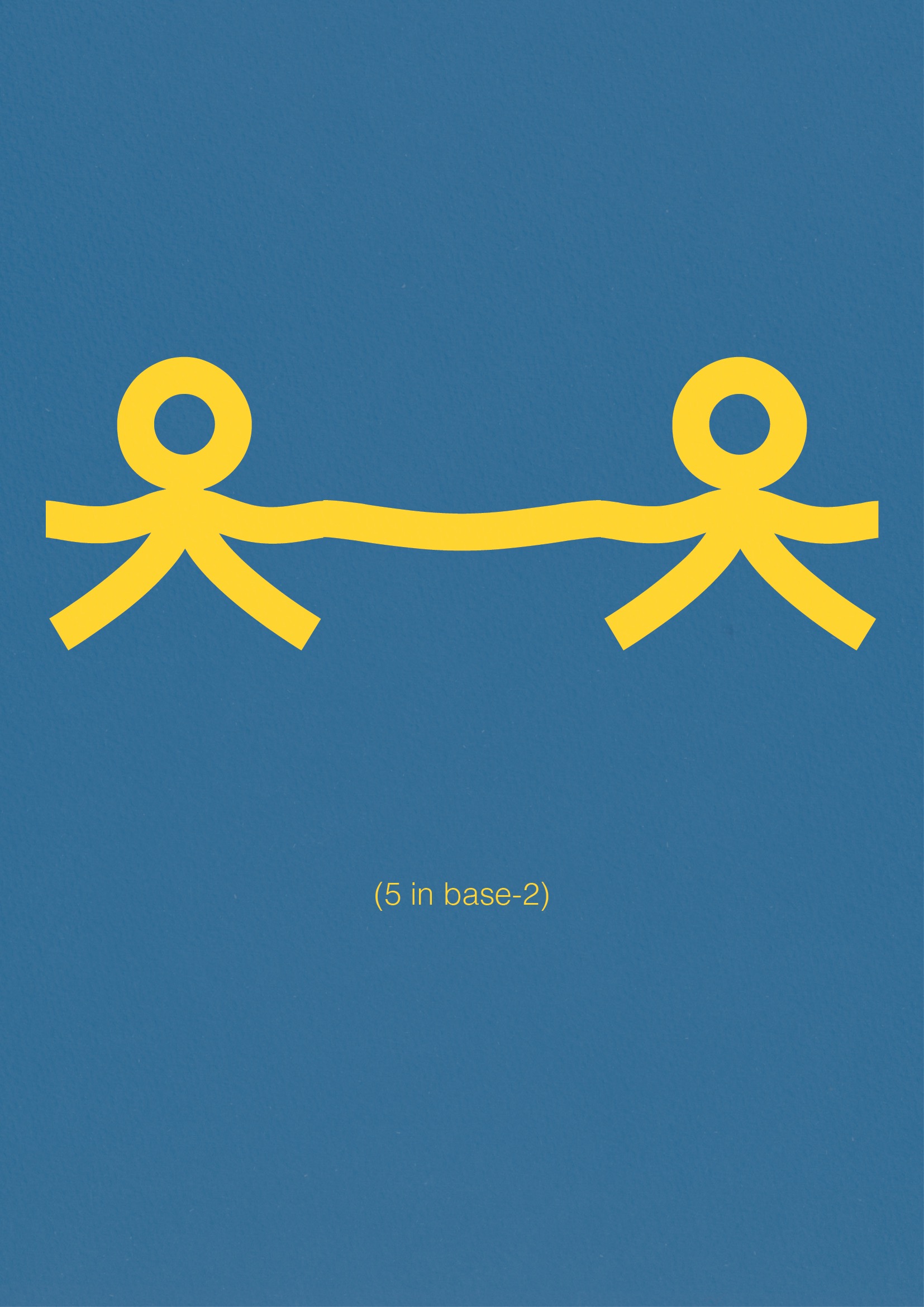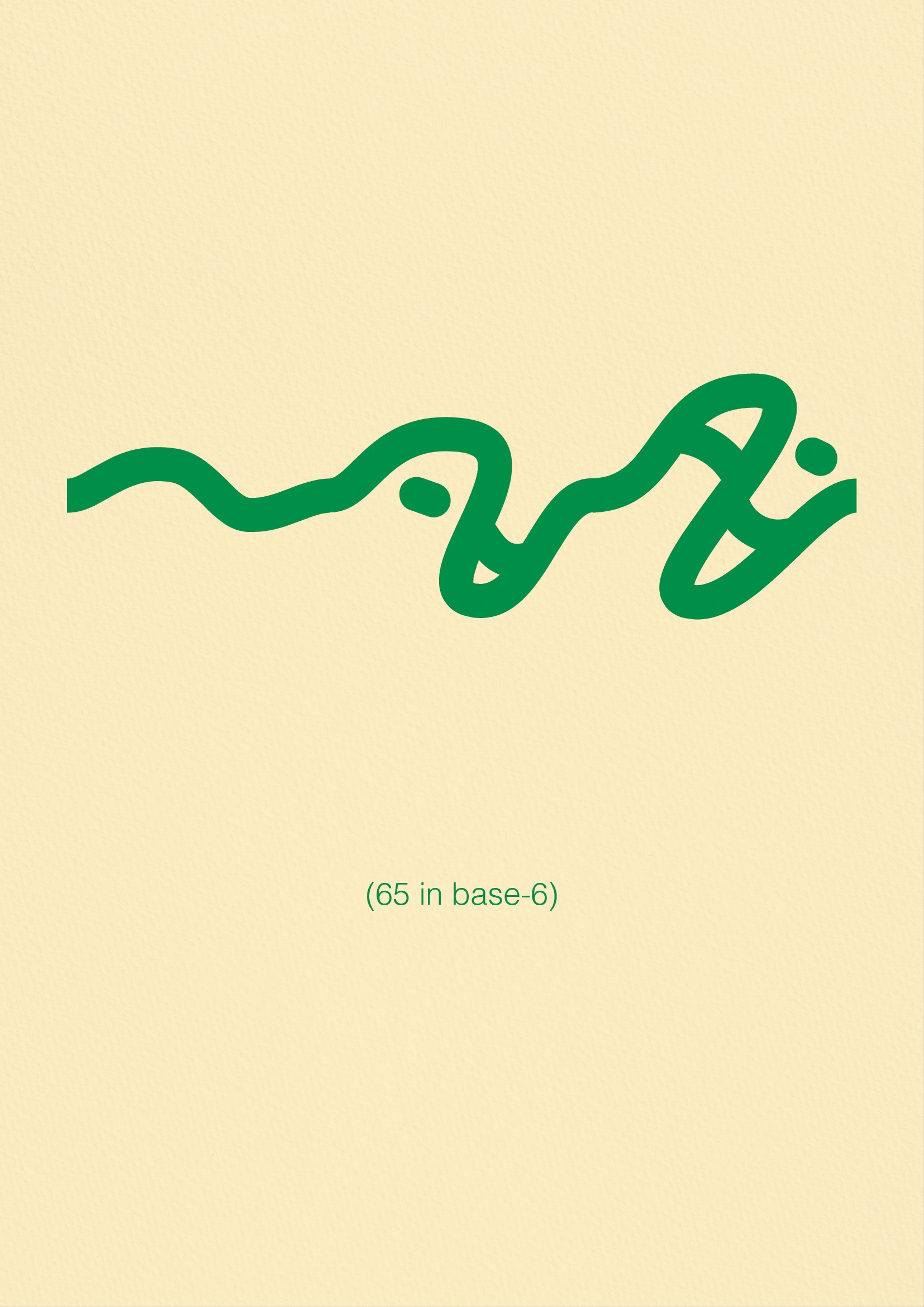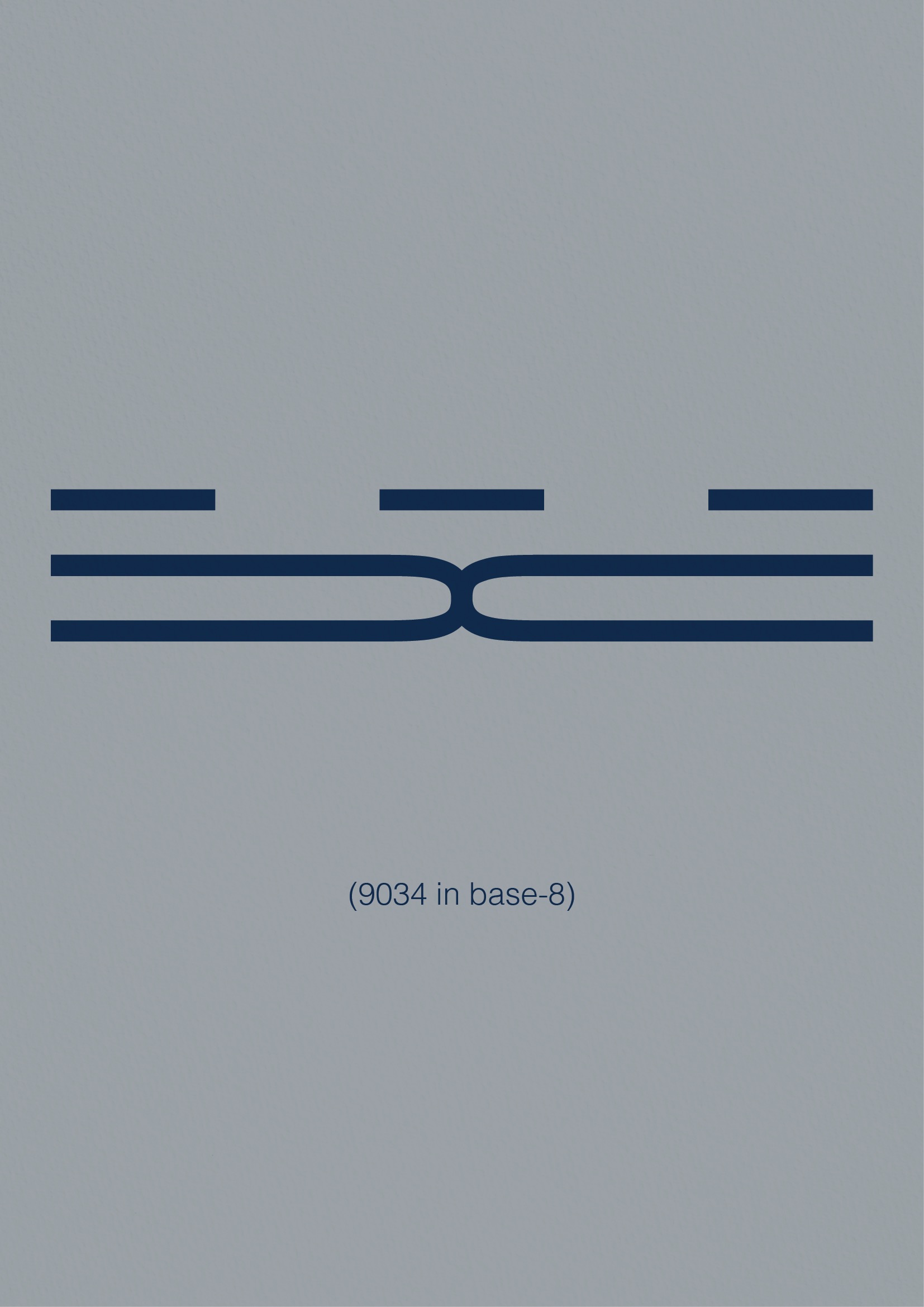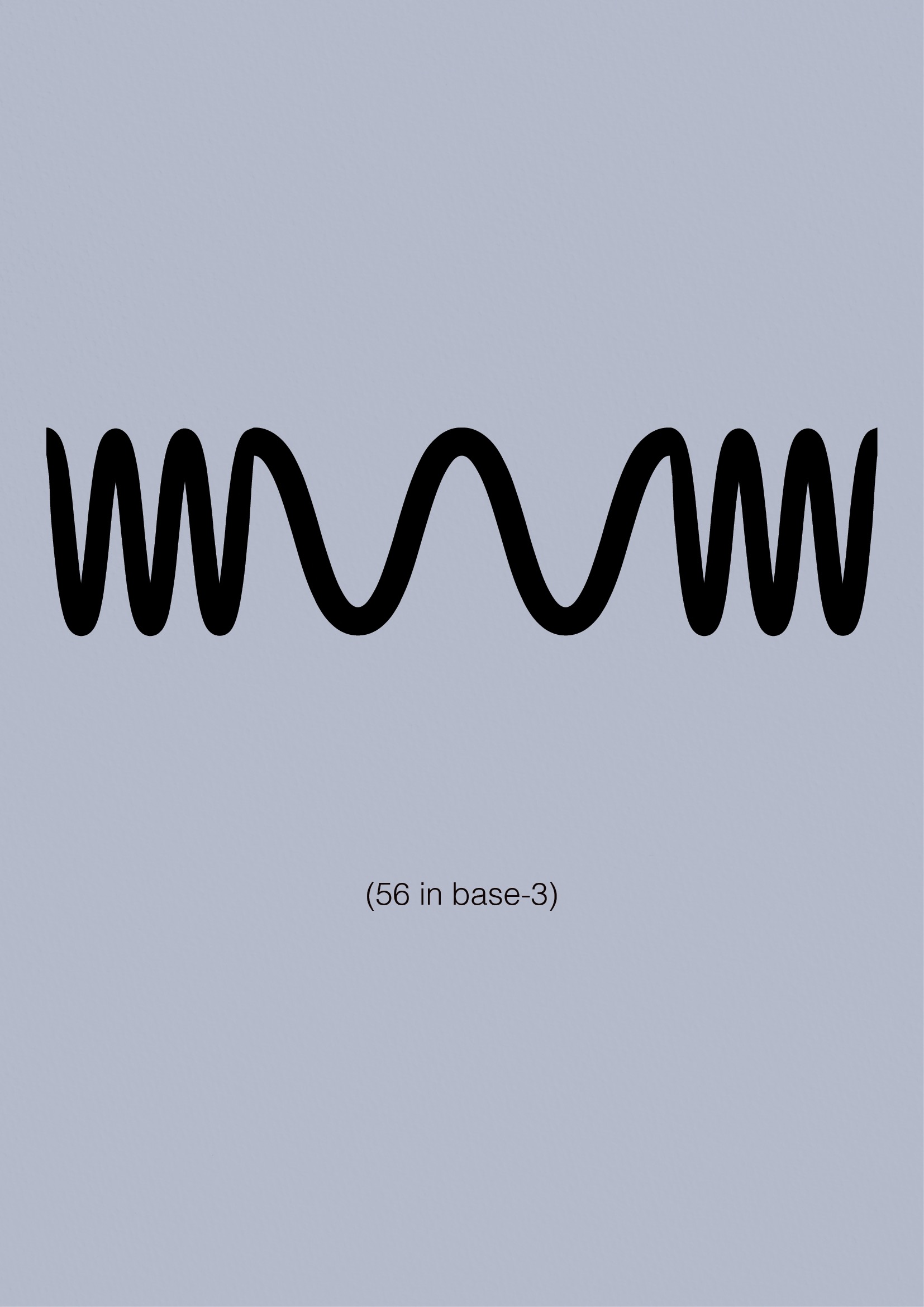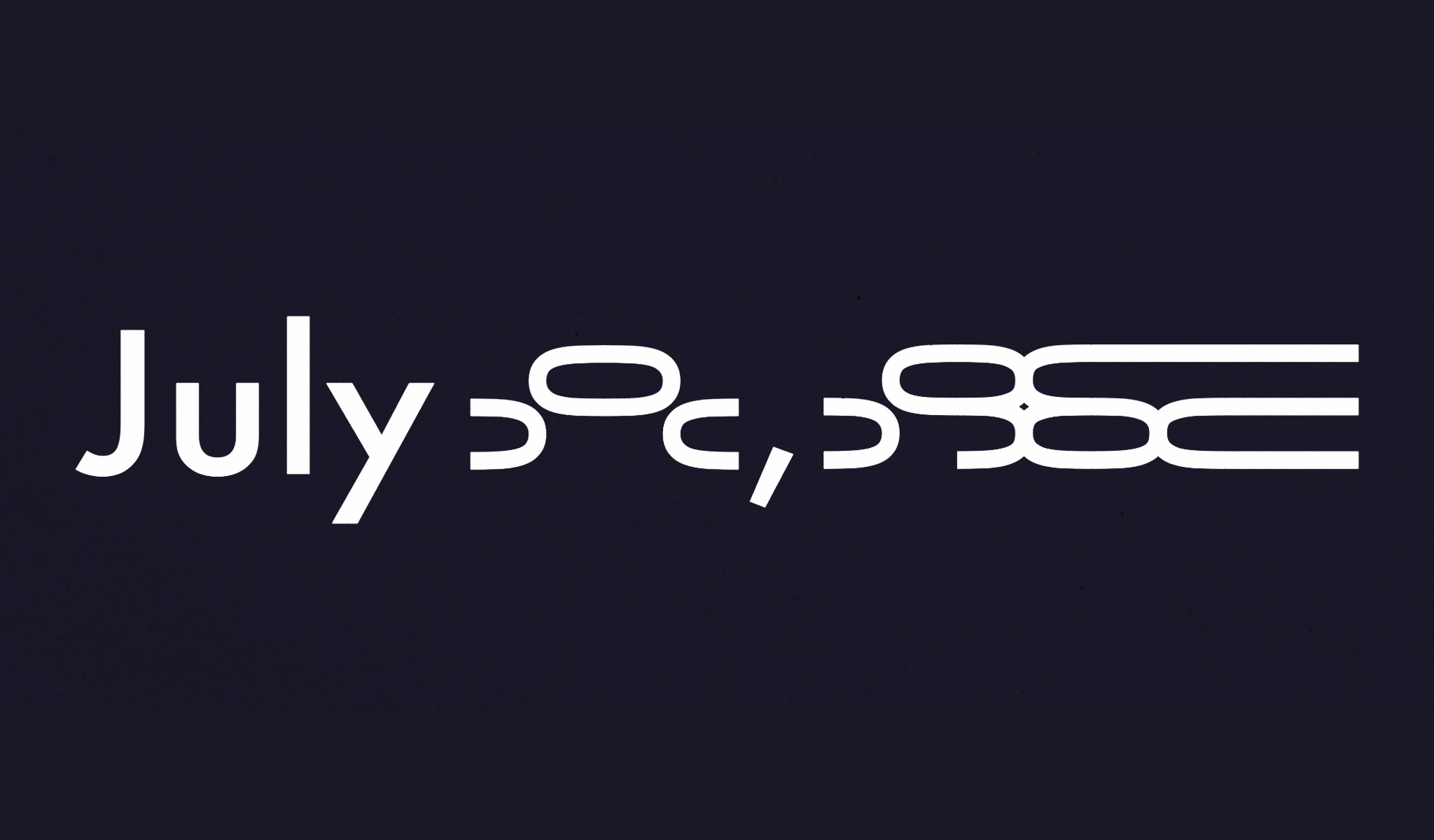
พิมพ์เลข 12 ลงไปในกล่องข้อความ แล้วเปลี่ยนฟอนต์ ตัวเลขบนหน้าจอกลายเป็น 1100
ไฟล์ยังเก็บเลข 12 ไว้เหมือนเดิม ไม่มีอะไรถูกแก้ สิ่งที่เปลี่ยนคือฟอนต์ และฟอนต์ตัวนั้นเพิ่งคำนวณเลขฐานสองให้เสร็จระหว่างที่นิ้วยังไม่ทันยกจากคีย์บอร์ด
ลิเกเจอร์ที่ไม่ได้ทำหน้าที่เดิม
Bases เป็นชุดฟอนต์จาก Performative Enumeration Systems โรงหล่อตัวอักษรทดลองที่ทำฟอนต์ซึ่งมีพฤติกรรม ไม่ใช่แค่มีรูปร่าง ในชุดนี้มีไฟล์แยกกันตามฐานเลข ตั้งแต่ฐานสองไปจนถึงฐานสิบ เลือกใช้ฐานไหนก็ติดตั้งไฟล์นั้น
กลไกข้างในใช้ลิเกเจอร์ของ OpenType ซึ่งเป็นของที่มีมานานแล้วในวงการตัวพิมพ์ หน้าที่ดั้งเดิมของมันคือความสวยงาม เวลาตัว f กับ i อยู่ติดกัน หัวของ f จะไปชนจุดของ i ช่างออกแบบจึงวาดตัว fi ขึ้นมาใหม่เป็นตัวเดียว แล้วบอกฟอนต์ว่าถ้าเจอสองตัวนี้เรียงกัน ให้สลับไปใช้ตัวที่วาดไว้
Bases ใช้กลไกเดียวกันนั้น แต่ไม่ได้ใช้เพื่อความสวย มันใช้ฟีเจอร์ชื่อ Contextual Alternates อ่านตัวเลขทั้งชุดที่พิมพ์ลงไป ไม่ใช่ทีละหลัก แล้วคำนวณค่าเดียวกันนั้นใหม่ในฐานที่เลือกไว้ ก่อนจะแสดงผลออกมา
ข้อจำกัดของมันตรงไปตรงมา ตัวเลขไม่เกินสี่หลักแปลงได้ถูกต้อง เกินกว่านั้นฟอนต์จะหั่นเป็นก้อนละสี่หลักแล้วแปลงทีละก้อน ซึ่งเป็นข้อจำกัดที่ตามมาจากการเขียนตรรกะทั้งหมดไว้ในตารางของไฟล์ฟอนต์
ตรรกะที่ไปอยู่ผิดที่
สิ่งที่ทำให้งานชุดนี้ค้างอยู่ในหัวหลังเลิกดู ไม่ใช่ตัวเลขที่เปลี่ยน แต่เป็นคำถามว่าความหมายไปอยู่ตรงไหน
ตามปกติ ฟอนต์คือชุดของรูปทรง เอกสารเก็บความหมาย ฟอนต์ทำหน้าที่แต่งตัวให้ความหมายนั้น เปลี่ยนฟอนต์คือเปลี่ยนเสื้อผ้า เนื้อความยังเท่าเดิม
ที่นี่เสื้อผ้ากลายเป็นคนพูด ค่าที่คนอ่านเห็นถูกกำหนดโดยไฟล์ฟอนต์ ไม่ใช่โดยเอกสาร ถ้าส่งไฟล์นั้นให้คนที่ไม่ได้ติดตั้งฟอนต์เดียวกัน เขาจะเห็นคนละเลขกับที่เราเห็น ทั้งที่เปิดไฟล์เดียวกัน
นักออกแบบคุ้นกับความคิดที่ว่าตัวพิมพ์มีน้ำเสียง ตัวหนาดูหนักแน่น ตัวเซริฟดูเป็นทางการ แต่ Bases ดันเส้นนั้นไปอีกขั้น ตัวพิมพ์ในที่นี้ไม่ได้มีน้ำเสียง มันมีความเห็น และความเห็นนั้นเปลี่ยนข้อเท็จจริงบนหน้ากระดาษได้จริง
เลขสิบเป็นเรื่องของนิ้วมือ
เหตุผลที่โครงการนี้เลือกเรื่องฐานเลข ไม่ใช่เพราะเลขฐานสองดูเท่ในสายตาคนทำงานดิจิทัล ทีมงานอ้างถึงระบบเลขเก่าอย่างอักษรลิ่มของเมโสโปเตเมีย และตัวเลขอีเจียนของกรีกยุคสำริด พร้อมกับแผนที่และไดอะแกรมเชิงโครงสร้าง
สิ่งที่ระบบเหล่านั้นเตือนเราคือ เลขฐานสิบไม่ใช่ความจริงทางคณิตศาสตร์ มันเป็นอุบัติเหตุทางกายภาพ คนมีสิบนิ้ว เราจึงนับเป็นสิบ ชาวบาบิโลนนับฐานหกสิบ และร่องรอยของมันยังอยู่กับเราทุกวันในหน้าปัดนาฬิกากับองศาของวงกลม
ตัวเลขที่เราเขียนมาทั้งชีวิตจึงไม่ใช่จำนวน มันเป็นสัญลักษณ์ที่ตกลงกันไว้ว่าจะแทนจำนวน และข้อตกลงนั้นเปลี่ยนได้ Bases แค่ทำให้ช่วงเวลาที่ข้อตกลงเปลี่ยนสั้นลงเหลือแค่การกดปุ่มเลือกฟอนต์
ในแง่หนึ่งมันคือการเอาระเบียบที่มองไม่เห็นออกมาวางให้เห็น แบบเดียวกับที่ grid system เป็นโครงที่คุมหน้ากระดาษ โดยที่ไม่มีใครเห็นเส้นของมันสักเส้น
ตัวพิมพ์ทำงานได้ดีที่สุดตอนที่ไม่มีใครสังเกตเห็นมัน นั่นคือสิ่งที่คนทำฟอนต์พูดกันมาตลอด งานชุดนี้ไม่ได้เถียงข้อนั้น มันแค่ถามต่อว่า ถ้าสิ่งที่มองไม่เห็นนั้นตัดสินใจแทนเราได้ด้วย เรายังอยากให้มันเงียบอยู่ไหม